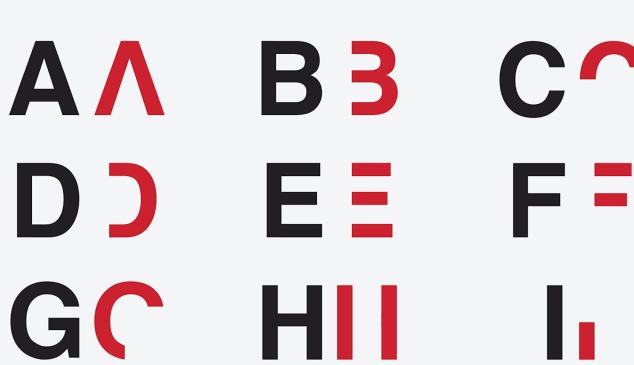
Cuando una persona con dislexia trata de leer un documento, la frustración termina por hacerse con el control al ser incapaz de identificar las letras que hay sobre el papel.
Un problema que resulta difícil de entender para las personas que no viven el día a día de este tipo de discapacidad que afecta a la lectura y que sufre entre el 3 y el 57% de la población. Pero que Daniel Britton ha querido ilustrar con una nueva línea de tipografía diseñada para replicar estas frustraciones.
Este diseño tipográfico fue creado a partir de la poda de un 40% de cada letra de la fuente Helvética. Cada carácter puede ser reconocido, aunque con cierto esfuerzo. De hecho, si se construyen palabras y frases con ellas, los lectores podrían tardar diez veces más de lo habitual en descifrarlas, según ha estimado Britton.
Aunque la tipografía no muestra exactamente lo que una persona disléxica ve, Britton ha tratado de generar una respuesta emocional similar a la que sienten aquellos que padecen trastornos de lectura.
“Lo que yo quería hacer era recrear o simular las emociones que se sienten durante la lectura al tener dislexia para resaltar lo frustrante que es tratar de leer algo simple”, ha explicado Britton quien fue diagnosticado con este tipo de trastorno durante la universidad.
Los anuncios que promueven la concienciación sobre la dislexia en Reino Unido ya han publicado esta nueva tipografía, mostrándosela también a los miembros de Parlamento británico.